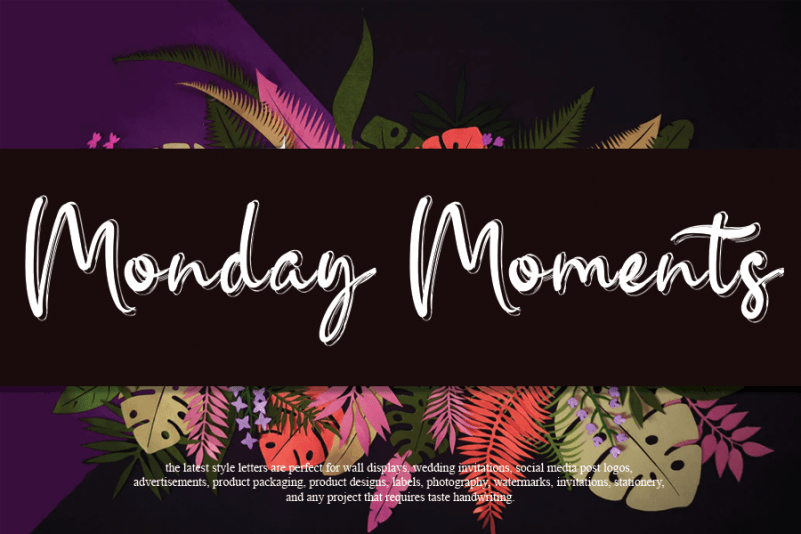
Monday Moments Script Font – Download Grátis
A fonte ‘Monday Moments Script Font’ é uma escolha perfeita para designers buscando um estilo suave e amigável que se destaca no mundo do design. Inspirada nos traços espontâneos da escrita manuscrita, esta fonte combina naturalidade com algo único, tornando-a ideal tanto para projetos digitais quanto impressos. Suas linhas delicadas e sua disposição fluida criam um sentido de conforto visual que não apenas complementará seu trabalho, mas também o deixará se sentindo imaginativo e criativo. Seja você uma marca jovem buscando criar conexões com seus clientes ou uma designer desbravando novos horizontes, ‘Monday Moments Script Font’ oferece a liberdade de imaginar designs que vão muito além da sua imaginação. O limite é apenas o seu potencial para expressar sua visão única e emotiva através do design.